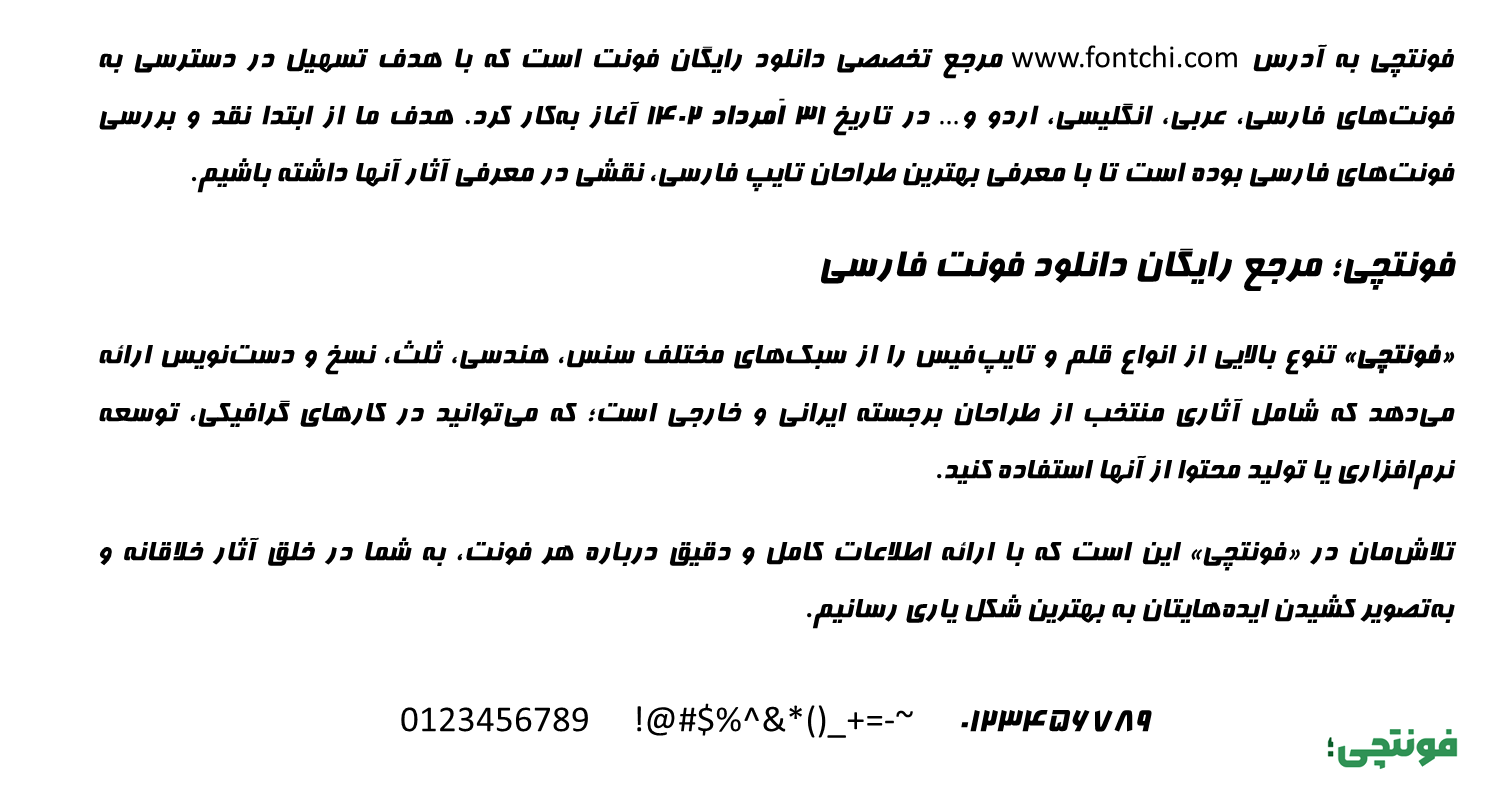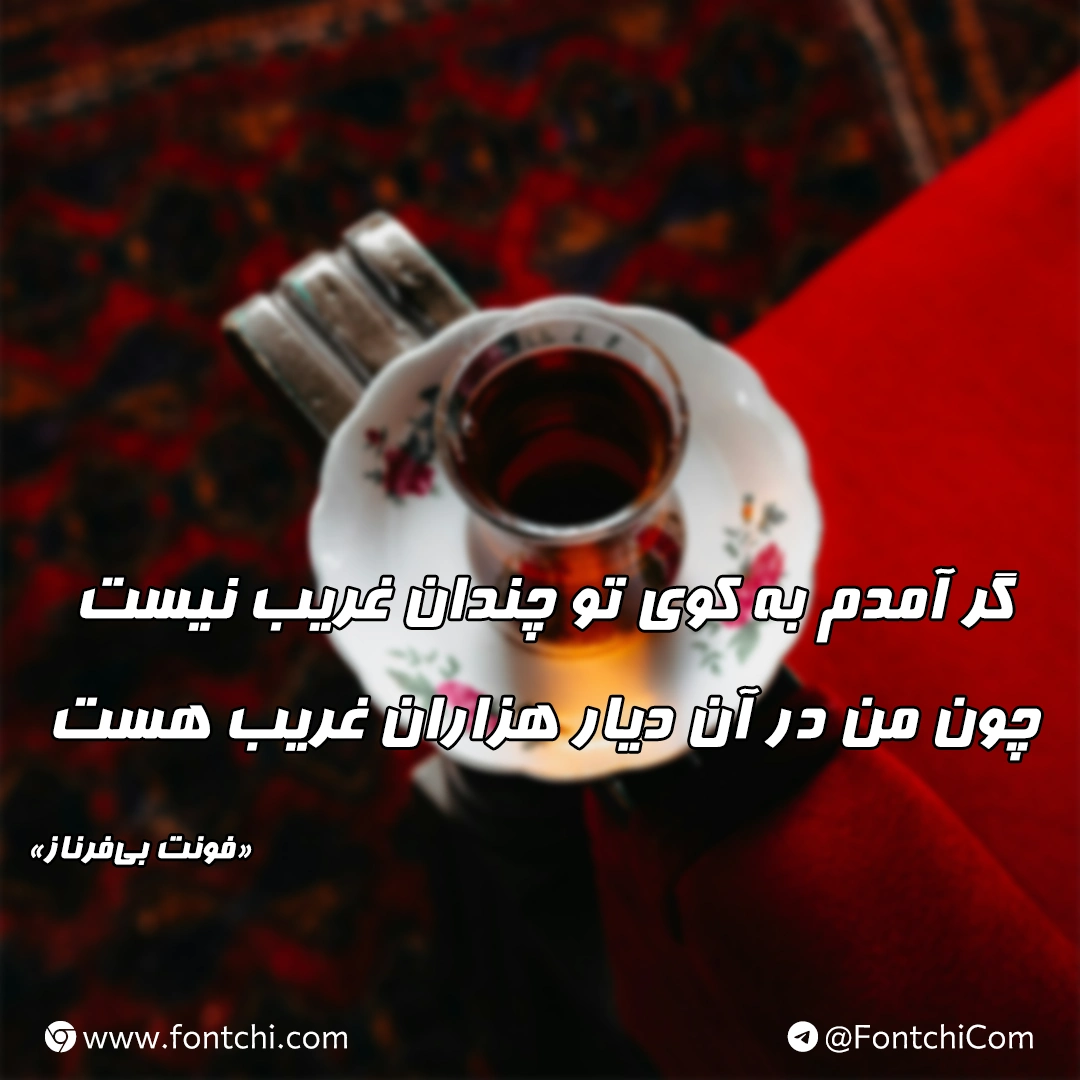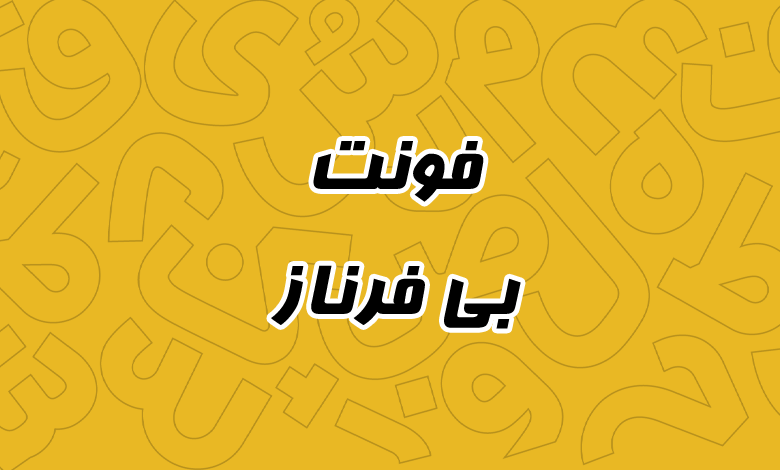
فونت بی فرناز (B Farnaz)
فونت بی فرناز یا فرناز (به انگلیسی: B Farnaz) یکی دیگر از قلمهای طراحی شده در دهه هفتاد است که به شکل آزاد و رایگان توسط برنا رایانه عرضه شده است. از این قلم به عنوان الگویی برای طراحی سایر فونتها همچون فونت لیانا استفاده شده است. در ادامه با دانلود فونت بی فرناز رایگان با شما همراه هستیم.
فونت b farnaz در یک وزن معمولی عرضه شده است و جزو محبوبترین سری فونتهای بی است که از آن برای کارهای نمایشی و عناوین استفاده میشود. این فونت فارسی رایگان دارای ظاهری هندسی است. این فونت شباهت زیادی به فونت بی مهر دارد، با این تفاوت که شکل رسمیتر و خشکتری دارد.
فونت بی فرناز از زبان فارسی پشتیبانی کاملی دارد. از آنجایی که با رسمخط عربی نیز یکسان هستند گلیفهای متفاوت این زبان همچون حروف «ک، ی، ه، ؤ، ئ» نیز به آن اضافه شده است. تنها کاستی این فونت برای زبان عربی مربوط به بخش اعداد میشود که فاقد گلیف استاندارد اعداد «۴۵۶» است و از اعداد فارسی استفاده خواهد شد. البته یک ایراد جزئی نیز برای عدد صفر فارسی وجود دارد که توخالی نیست و به شکل نقطه است؛ شکل نقطه عدد عربی است.
دیگر زبان پشتیبانی شده در فونت فرناز انگلیسی است. اما برای این زبان طراحی اختصاصی روی این فونت اعمال نشده و از فونت پیشفرض سیستم عامل برای حروف لاتین استفاده خواهد شد. بنابراین اگر به دنبال گزینه مناسب و نزدیک هستید، میتوانید از سایر فونتهای انگلیسی رایگان که هماهنگ با این قلم هستند استفاده کنید.
طراحی حروف در فونت فرناز دارای ظاهری هندسی است؛ به شکلی که تمامی حروف دارای ظاهری به شکل مربعی و با زوایای تقریبا ۹۰ درجه هستند. نقاط نیز بهمنظور هماهنگی با این سبک به شکل مربعی طراحی شدهاند. به مقدار خیلی کمی نیز حروف ظاهر ایتالیک دارند.
ظاهر فونت بی فرناز بولد است؛ با اینکه وزن آن Regular است. این نوع فونتها برای کارهای نمایشی که نیاز به فونتی ضخیم داریم مناسب هستند. برای استفاده در عناوین و تبلیغات گرفته تا فونت جلد روی کتاب و فونت برای کاور شبکههای اجتماعی مناسب هستند. بنابراین اگر نیاز به فونت رایگان برای اینشات دارید میتواند انتخاب خوبی باشد.